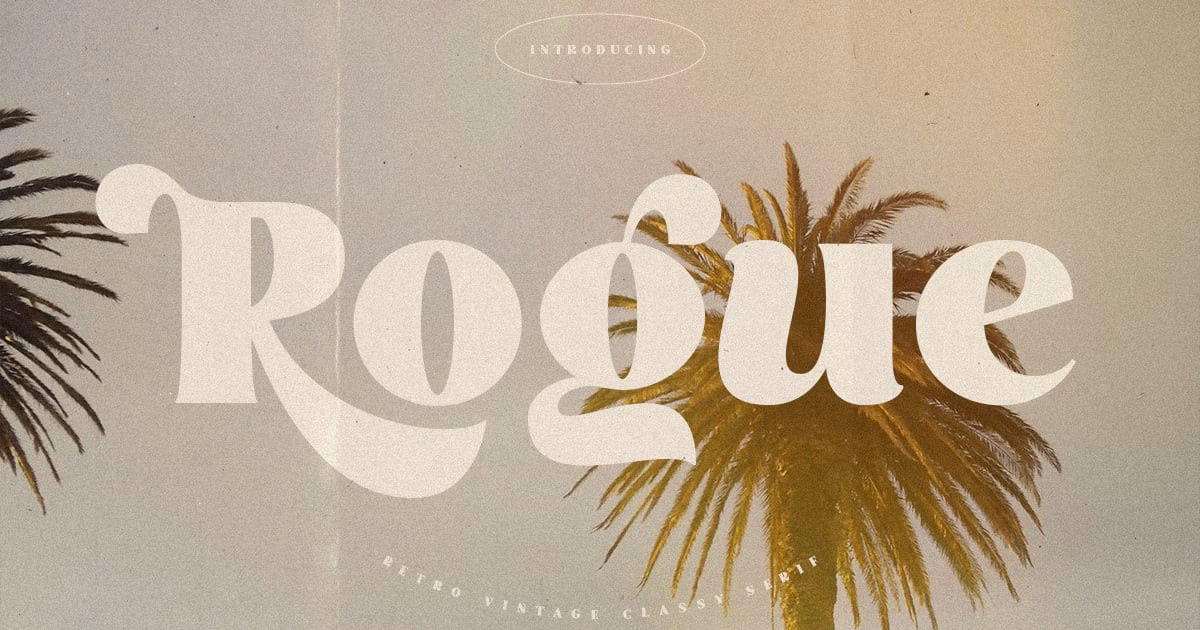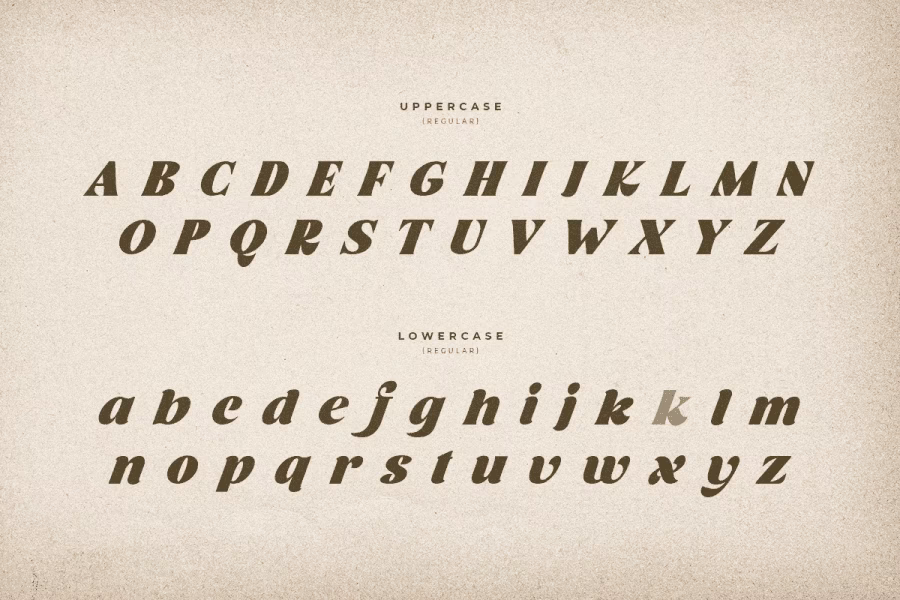
En el vasto universo del desarrollo de videojuegos, a menudo centramos nuestra atención en los gráficos deslumbrantes, las mecánicas de juego innovadoras o las bandas sonoras épicas. Sin embargo, existe un componente fundamental, un héroe silencioso que trabaja en las sombras para dar forma a la identidad y la atmósfera de un juego: la tipografía. No es solo texto en una pantalla; es la voz visual de un mundo, y pocas veces encontramos un ejemplo tan evocador como la fuente gratuita "Rogue". A través de su nombre y diseño, nos invita a explorar no solo sus usos prácticos, sino también la profunda conexión entre las letras y la experiencia lúdica, especialmente con uno de los géneros más icónicos de la industria.
¿Qué es la Tipografía y Por Qué Importa en los Videojuegos?
Antes de sumergirnos en las particularidades de la fuente Rogue, es crucial entender el papel que juega la tipografía. Lejos de ser un mero adorno, la elección de una fuente impacta directamente en la experiencia del jugador. Una tipografía adecuada puede:
- Establecer el Tono: ¿Estamos en un reino de fantasía medieval, en una distopía ciberpunk o en una aventura de dibujos animados? La fuente del título, los menús y los diálogos es a menudo la primera pista que recibe el jugador. Pensemos en la fuente gótica y ornamentada de la saga Diablo o en la tipografía pixelada y nostálgica de Stardew Valley.
- Mejorar la Legibilidad: En juegos con mucho texto, como los RPGs o las novelas visuales, una fuente clara y legible es indispensable. Una mala elección puede causar fatiga visual y frustración, sacando al jugador de la inmersión.
- Construir una Marca: La tipografía es una parte esencial de la identidad visual de un juego. El logo de Grand Theft Auto, con su fuente "Pricedown", es instantáneamente reconocible y evoca una sensación de cultura pop americana y audacia.
- Guiar al Jugador: A través de la jerarquía visual (diferentes tamaños, pesos y estilos de fuente), la tipografía guía al jugador a través de los menús y la interfaz, indicando qué es un título, qué es un botón y qué es información secundaria.
En resumen, la tipografía no es solo para leer, es para sentir. Es una herramienta de diseño tan poderosa como la paleta de colores o el diseño de personajes.
Rogue: Una Fuente con Nombre y Carácter
En este contexto emerge la "Rogue Free Typeface", una creación del diseñador Andreas Leonidu. Esta fuente no es una más del montón; su diseño y su nombre la convierten en un caso de estudio fascinante para cualquier desarrollador o aficionado a los videojuegos. Se caracteriza por un diseño limpio y nítido, concebida como una fuente de visualización (display font). Esto significa que su principal fortaleza reside en su impacto visual en textos cortos y de gran tamaño, como títulos, carteles, logos y encabezados.
Sus líneas definidas y su estética moderna pero contundente la hacen increíblemente versátil. El propio creador sugiere su uso para publicidad de equipos deportivos en redes sociales o para la creación de logotipos y branding. Su naturaleza afilada y directa comunica confianza, acción y un toque de rebeldía. Y es precisamente esa última palabra, "rebeldía", la que nos lleva a su conexión más profunda con el mundo de los videojuegos.
El Vínculo Inevitable: La Fuente "Rogue" y el Género Rogue-like
No se puede escuchar la palabra "Rogue" en el contexto de los videojuegos sin pensar inmediatamente en el legendario género Rogue-like. Nacido del juego Rogue de 1980, este género se define por características clave como la generación procedural de niveles, la muerte permanente (permadeath) y una alta dificultad que exige estrategia y adaptabilidad.
¿Es una coincidencia que una fuente con un diseño tan asertivo y agudo lleve este nombre? Probablemente, pero la conexión es demasiado perfecta para ignorarla. Un "rogue" (pícaro, en español) es un personaje individualista, que se sale de la norma, que sobrevive gracias a su ingenio y astucia. La fuente Rogue, con su diseño sin adornos innecesarios y su impacto directo, parece encarnar visualmente este espíritu. Un desarrollador que esté creando un nuevo juego Rogue-like podría encontrar en esta tipografía el aliado perfecto para su logo y material promocional. Comunica al instante la esencia del género: un desafío directo, sin rodeos, donde cada decisión es nítida y sus consecuencias, permanentes.
Imaginemos el título de un juego como "Cosmic Rogue" o "Dungeon Rogue" escrito con esta fuente. La tipografía no solo deletrea el nombre, sino que también grita la promesa de una experiencia intensa, precisa y desafiante, preparando mentalmente al jugador para lo que le espera.